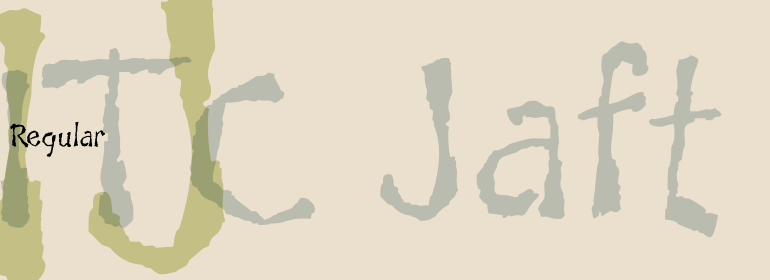
ITC Jaft™
字体品牌: ITC(Monotype) 设计师:Marciuliano,Frank 字体分类:衬线体 字体属性:外文 字符集:Unicode 发布时间: 2018
ITC Jaft是纽约设计师Frank Marciuliano的作品,这是一款富有冒险精神、充满活力的展示字体。 Marciuliano最初是为《纽约时报》设计了一家族海报。字母是用竹笔绘制后再进行填充以创作出不寻常的角度,从而使ITC Jaft看起来非常独特。
ITC Jaft is the work of New York designer Frank Marciuliano, an adventurous, energetic display typeface. It began with a series of posters designed by Marciuliano for the New York Times. The lettering was drawn with a bamboo pen and then filled in to create the unusual angles that give ITC Jaft its unique look.